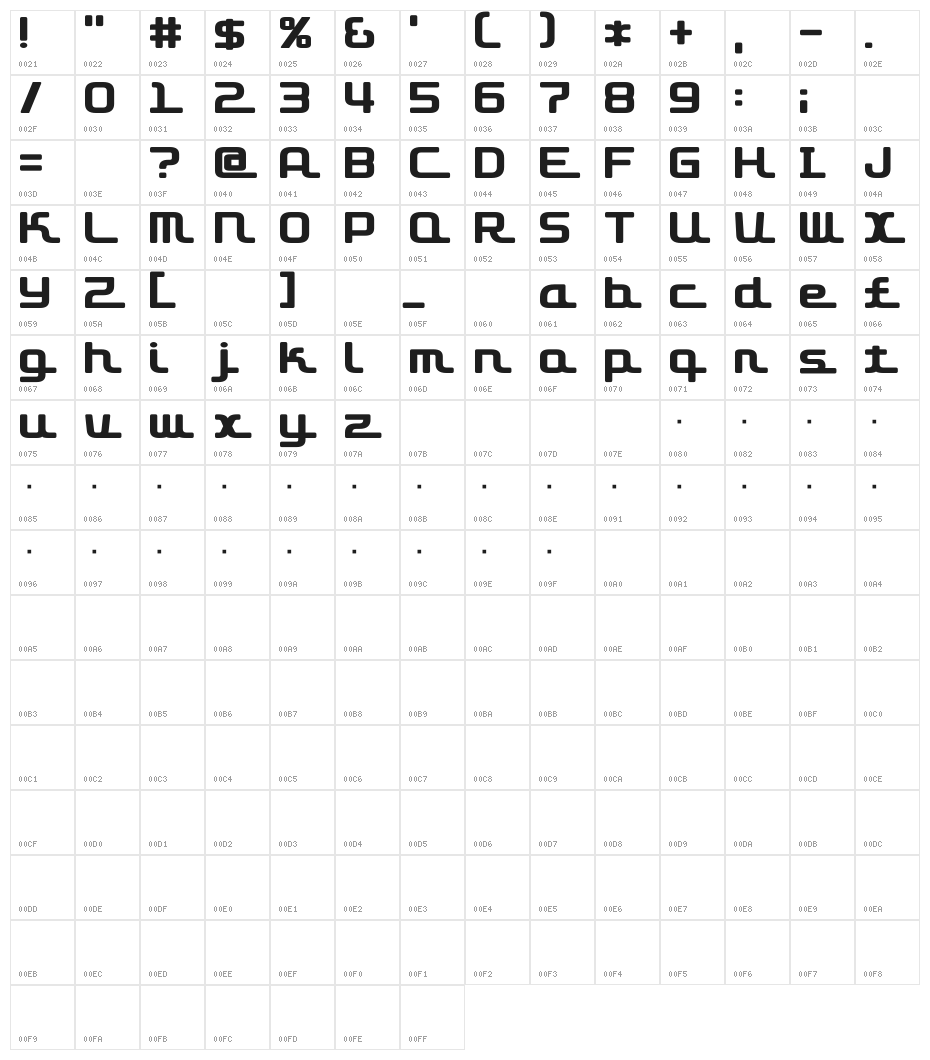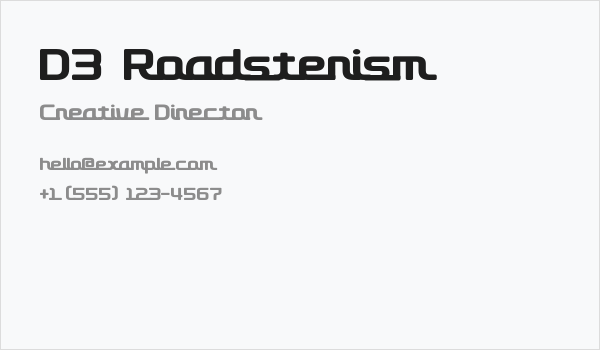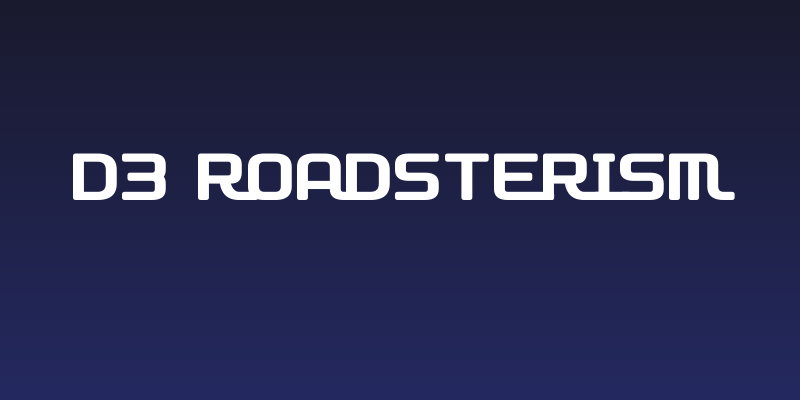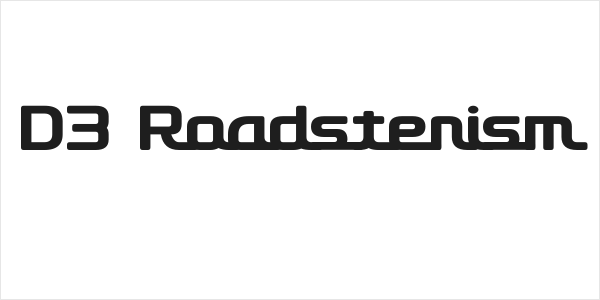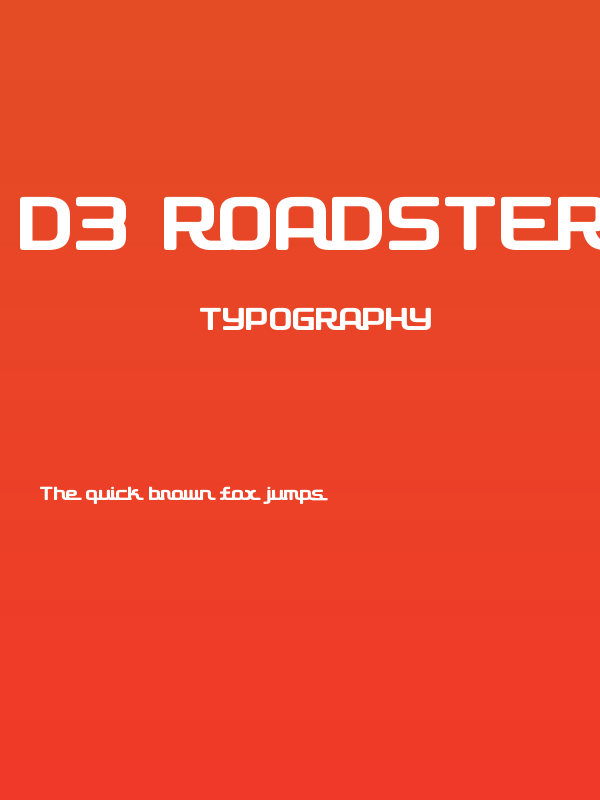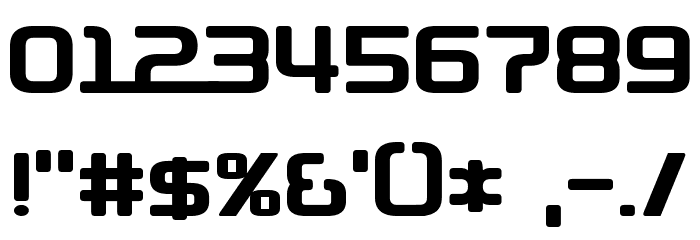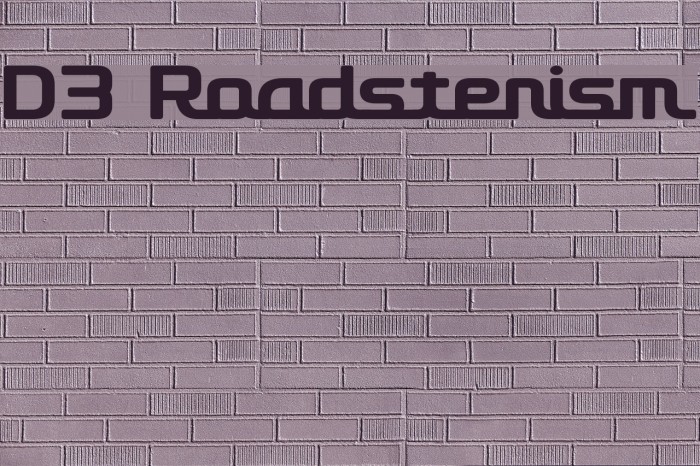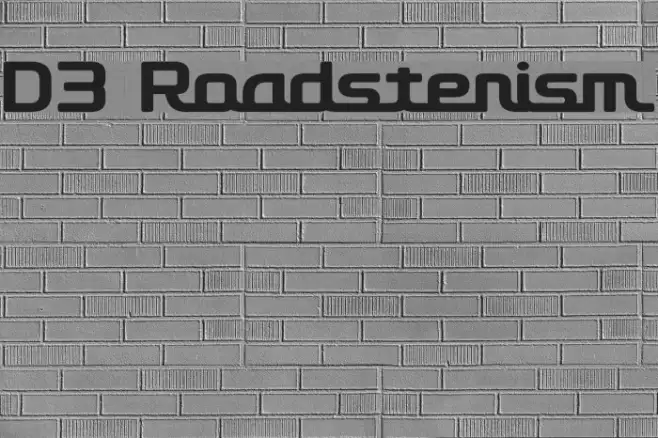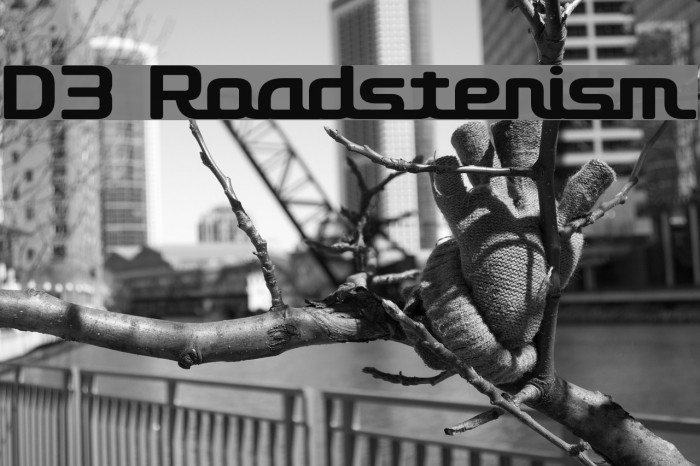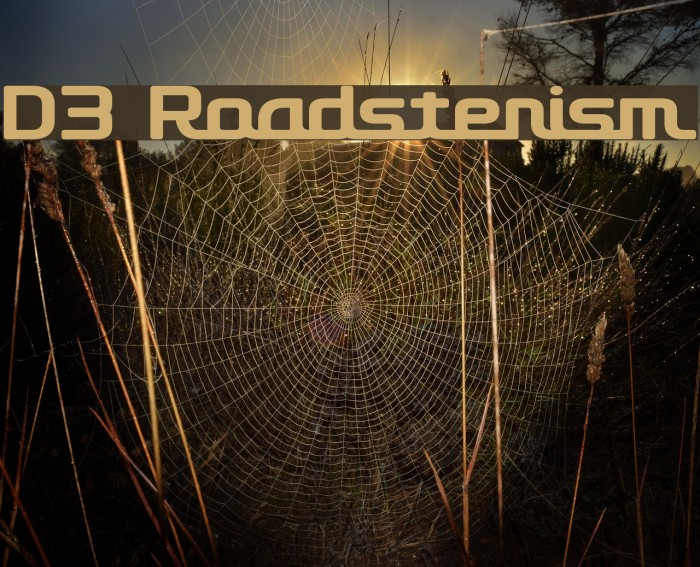
D3 Roadsterism Font
✎ Futuristic
| Anwendungsfall | Logos, Headlines, Digital Interfaces |
| Vorgeschlagene Projekte | Ideal for tech branding, modern advertising, digital interfaces, and futuristic-themed projects. |